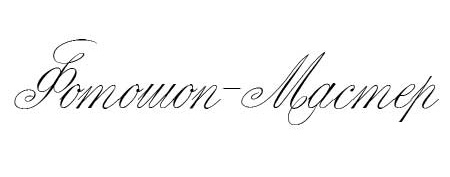
Скачала всё нормально! Но почему каждая буква заглавная? В чём секрет? В образце по-другому!
А это кириллический шрифт?
шрифт очень красивый, но он не поддерживает "ь" (мягкий знак)
прям как пером)))))отлично((спасибо))))